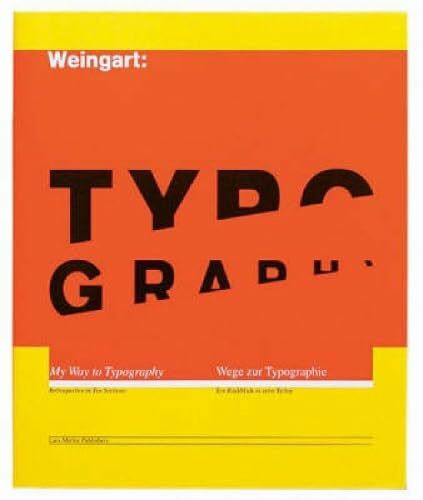
Typography: My way to Typography / Mein Weg zur Typographie
"Typography: My Way to Typography / Mein Weg zur Typographie" von C. Schelbert ist ein Buch, das sich mit der Kunst und Technik der Typografie auseinandersetzt. Der Autor teilt seine persönliche Reise und Erfahrungen in diesem Bereich, angefangen bei den Grundlagen bis hin zu fortgeschrittenen Techniken. Das Buch bietet Einblicke in die Geschichte der Typografie, die Entwicklung von Schriftarten und deren Anwendung im Design. Es enthält praktische Anleitungen und Tipps für Designer und Interessierte, um ihre eigenen typografischen Fähigkeiten zu verbessern. Durch illustrative Beispiele und Fallstudien vermittelt Schelbert sowohl theoretisches Wissen als auch praktische Anwendungen, um ein tieferes Verständnis für die Bedeutung und Wirkung von Schrift im visuellen Kommunikationsdesign zu schaffen.